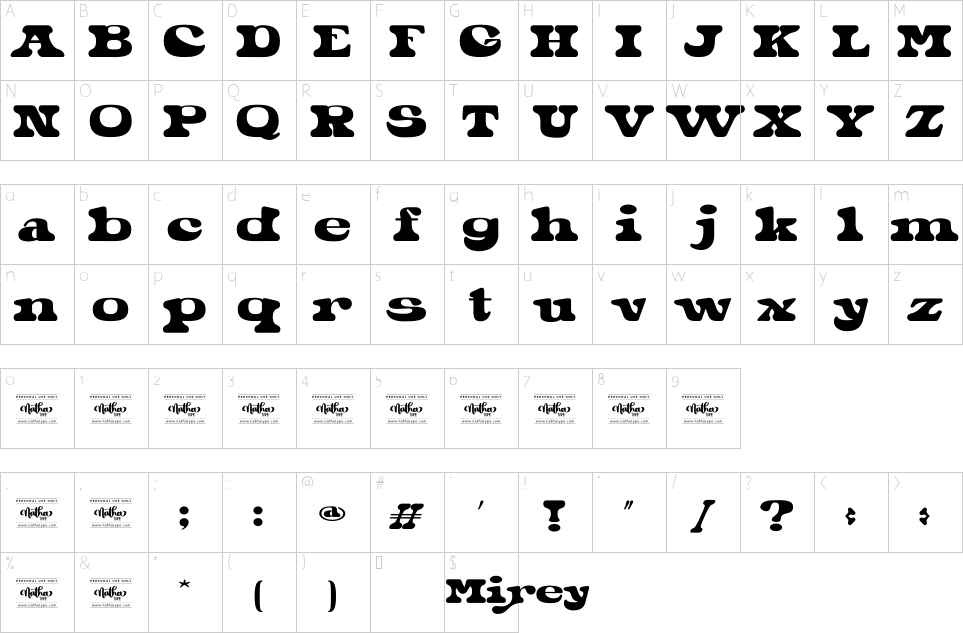
Descubra uma nova fonte grátis e única para seus projetos de design. Introduzimos Mirey, uma fonte de Natha Type, disponível para download tanto em Windows quanto Mac. Mirey foi projetada para oferecer uma opção diversificada e elegante para estilos de design variados. Suas linhas fluidas e sutis garantem um texto profissional e sofisticado. Este é um exemplo ideal para designers que buscam uma fonte moderna e versátil para usar em qualquer projeto, desde sites pessoais até portfolios de design. Com um download contínuo de 1,115 vezes, é claro que Mirey está ganhando popularidade entre designers ao redor do mundo. Descubra por si mesmo a qualidade de Mirey e seu potencial para tornar seus projetos destacadamente únicos.